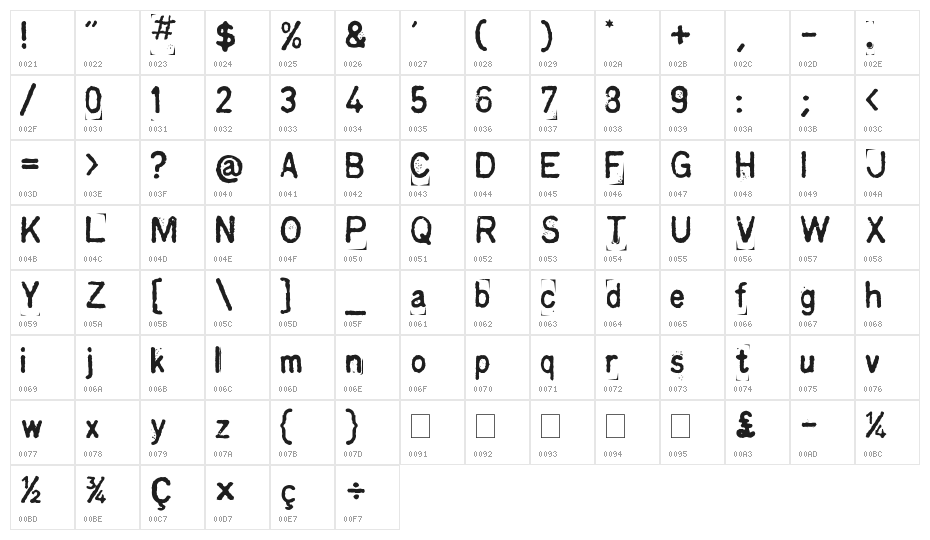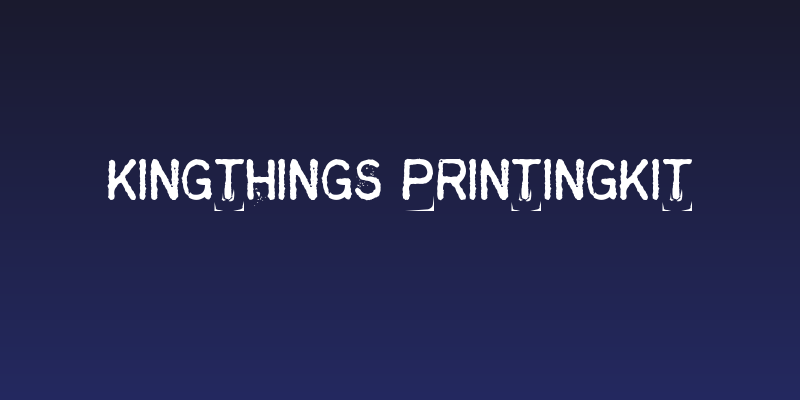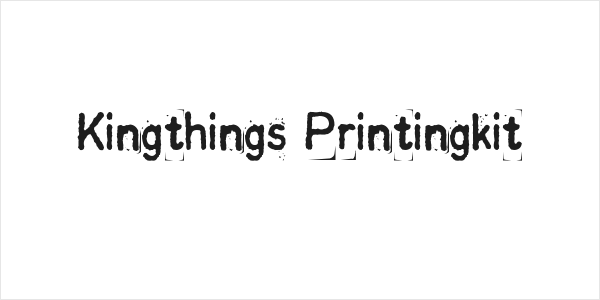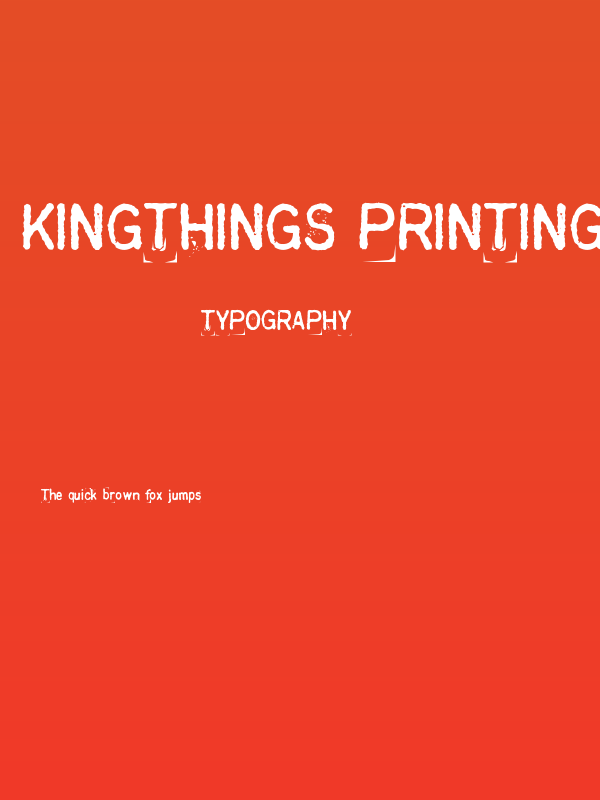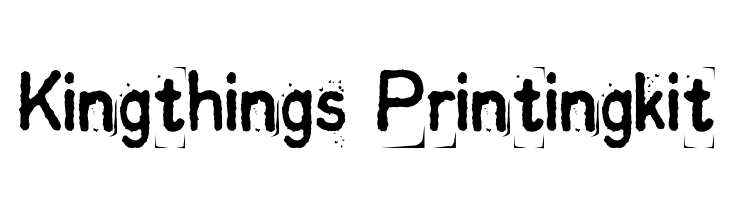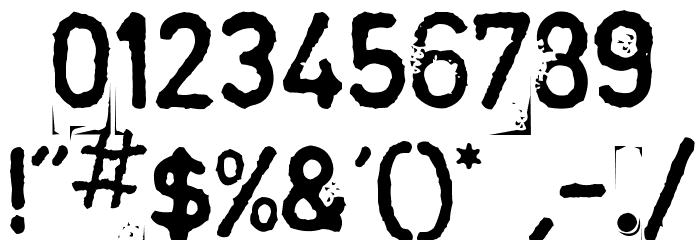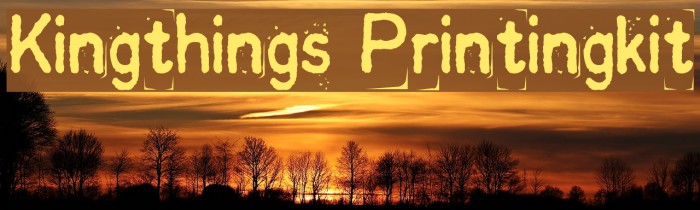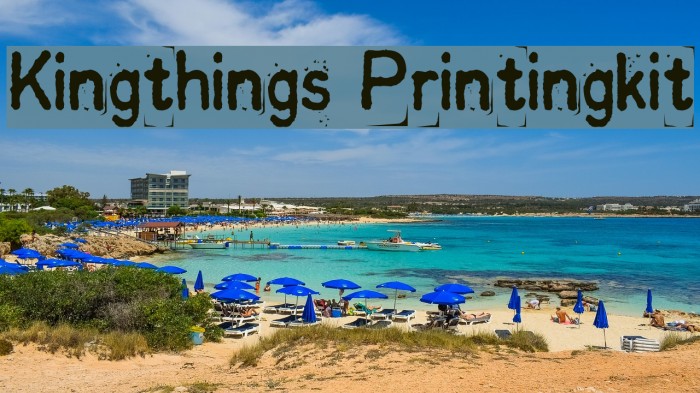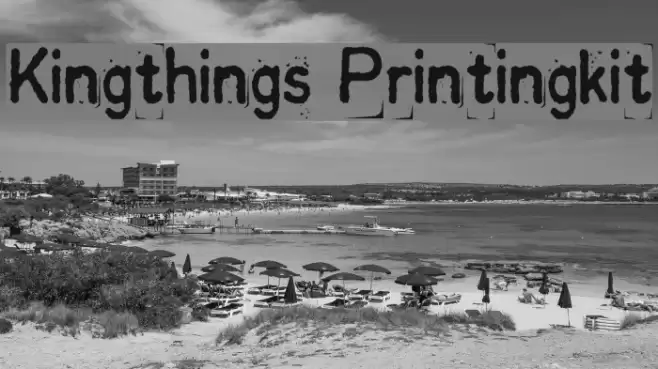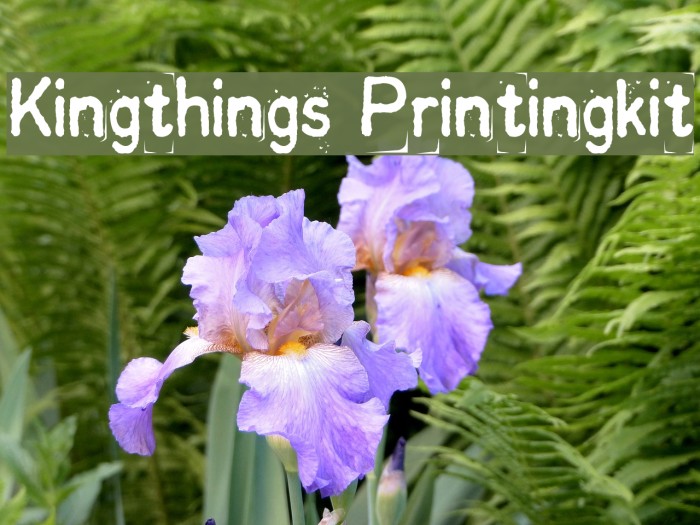
Kingthings Printingkit Font
✎ Distorted Eroded
| Projetos propostos | Ideal for creative projects such as posters, album covers, artistic branding, and any design requiring a bold, handcrafted aesthetic. |